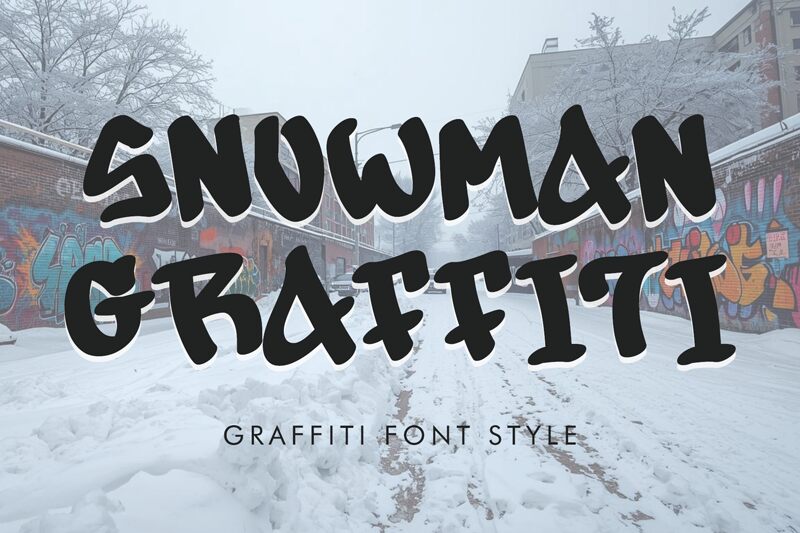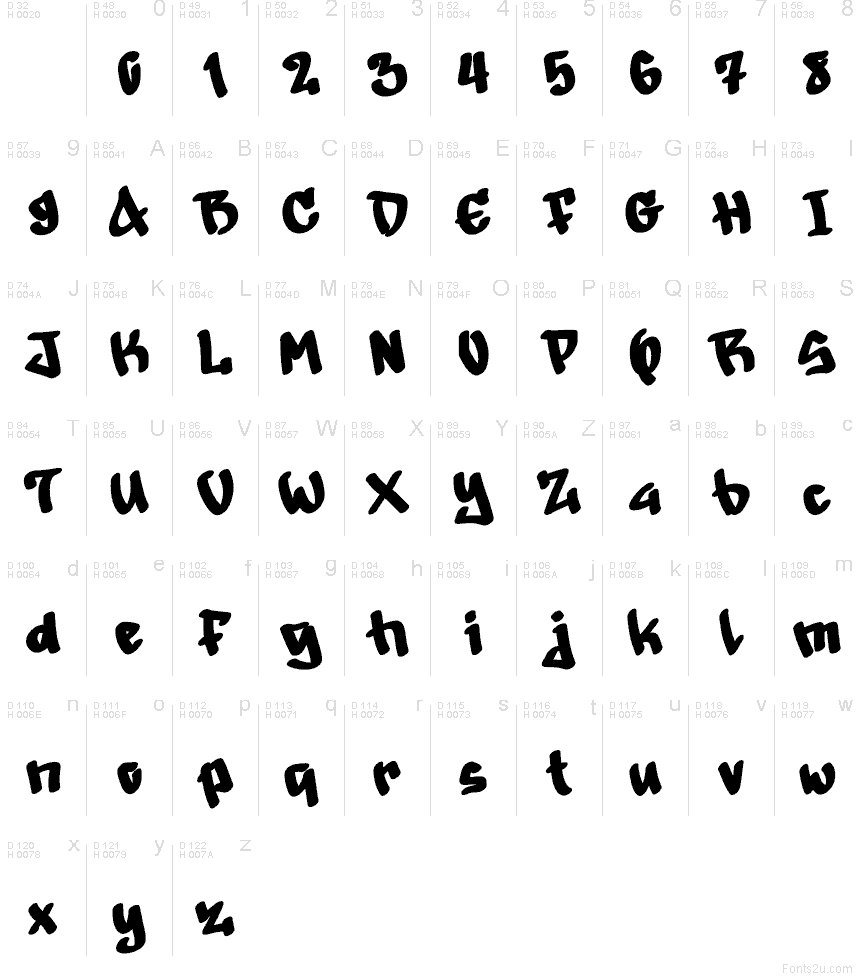
Snowman Graffiti Demo
Snowman Graffiti é uma fonte de grafite gratuita, com traços arredondados feitos à mão e uma cadência suave que remete à arte com spray. As letras possuem curvas e contornos irregulares que parecem desenhados à mão, conferindo ao conjunto um caráter de arte urbana sem bordas afiadas.
Snowman Graffiti funciona muito bem em títulos de cartazes, capas de álbuns, designs de adesivos, flyers de eventos e artes para redes sociais que precisam de um ar urbano e casual. Esta fonte gratuita também se adapta bem a logotipos, produtos de merchandising e legendas decorativas onde essas formas arredondadas transmitem uma mensagem com um toque mais informal e artesanal.